18 phần dự thi là 18 bức tranh vô cùng sinh động được các cô giáo vẽ lên bằng phấn, bảng và những con chữ uốn lượn. Những bức "tranh chữ" của các cô giáo đến từ trường Tiểu học Trưng Vương, tỉnh Quảng Trị đang tạo lên cơn sốt yêu thích trên MXH.
Cổ nhân ta có câu "nét chữ, nết người". Theo đó, chữ viết ngoài việc dùng làm thông điệp truyền tải thông tin còn biểu hiện ra trạng thái nội tâm của một người, do đó rèn chữ cũng như rèn người.
Bởi vậy mà dẫu trong thời đại smartphone ngày nay, cùng với sự phát triển của các công cụ đắc lực hỗ trợ soạn thảo văn bản, quan niệm “nét chữ, nết người” vẫn còn giữ nguyên giá trị của nó.
Còn nhớ khi vừa chập chững bước chân vào lớp 1, bài học đầu tiên mà chúng ta được dạy chính là luyện chữ.
Trong ký ức của rất nhiều người, đó là những chuỗi ngày dài mệt mỏi với những phần luyện tập lặp đi, lặp lại đến khó chịu mà không biết đến bao giờ chữ mới đẹp được như chữ cô giáo?
Mới đây, trên MXH vừa xuất hiện hình ảnh bài dự thi viết chữ đẹp của 18 cô giáo tiểu học ở Quảng Trị khiến cư dân mạng vô cùng thích thú. 18 phần dự thi là 18 bức tranh được các cô giáo vẽ lên bằng phấn, bảng và những con chữ như biết uốn lượn!
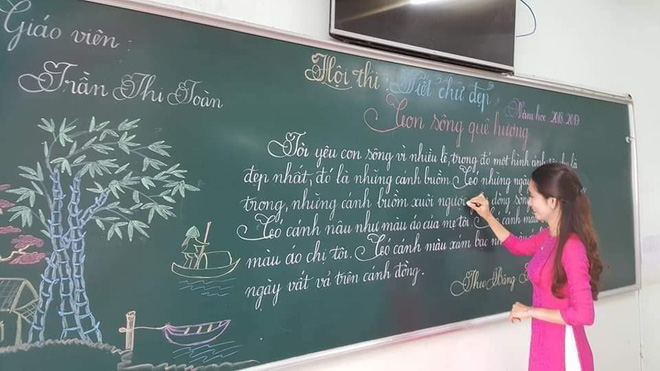
Con sông quê hương
Bên cạnh nét chữ đẹp miễn chê, các phần dự thi của các cô giáo còn đặc biệt gây ấn tượng bởi tính sáng tạo và nghệ thuật.
Mỗi bài thơ với chủ đề con người, quê hương, đất nước đều được họa thêm hoạt cảnh, "font chữ" cũng được các cô tùy biến cho phù hợp và vô cùng sinh động!
Chùm ảnh sau khi được chia sẻ lên MXH đã lập tức tạo lên cơn sốt yêu thích trong cộng đồng mạng. Những bức "tranh chữ" của các cô giáo Tiểu học Trưng Vương qua đó nhận về hàng nghìn lượt like chỉ trong một thời gian ngắn và hiện đang viral mạnh mẽ!
Lại nhớ hồi đi học, nếu ai hỏi tôi cái gì đẹp nhất, tôi sẽ chẳng ngần ngại mà trả lời: Chữ cô giáo! Hãy cùng chiêm ngưỡng 18 tác phẩm tuyệt đẹp này nhé!